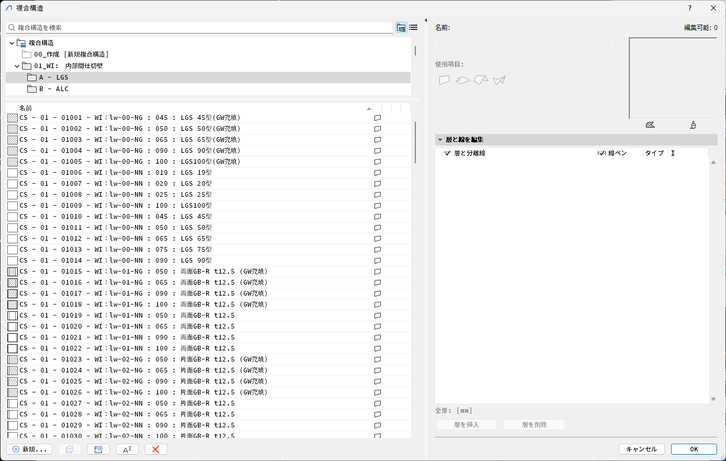
ARCHICADで使用しているフォントを環境設定で等幅フォントも選べるようにしてほしい
細かいですが、現状ARCHICADで使用されているフォントはプロポーショナルフォントで視認性は良いのですが、属性をしっかりと命名規則を整理して管理するには等幅フォントのほうが向いているかと思います。大量の属性を管理するBIMマネージャーの立場としては管理がしにくいのが困っていまして、環境設定でプロポーショナルフォントと等幅フォントを選択できるようになるといいなと思っています。
の値を任意のフォントに変更するとレイヤーも含んだフォントが変わりますね。
この Large Dialog Font Name だけ変更すれば問題なさそうです。
コーディングで良く使用されるらしい「源ノ角ゴシック Code JP」をインストールして、
Large Dialog Font Sizeを「17」にしてみたところ、結構いい感じにまとまりました。
そもそも、等幅フォントにしたいかなんて相当マニアックな悩みですが、、、、
わりかし、違和感ないかなって思います。しばらくこれで使ってみます!!